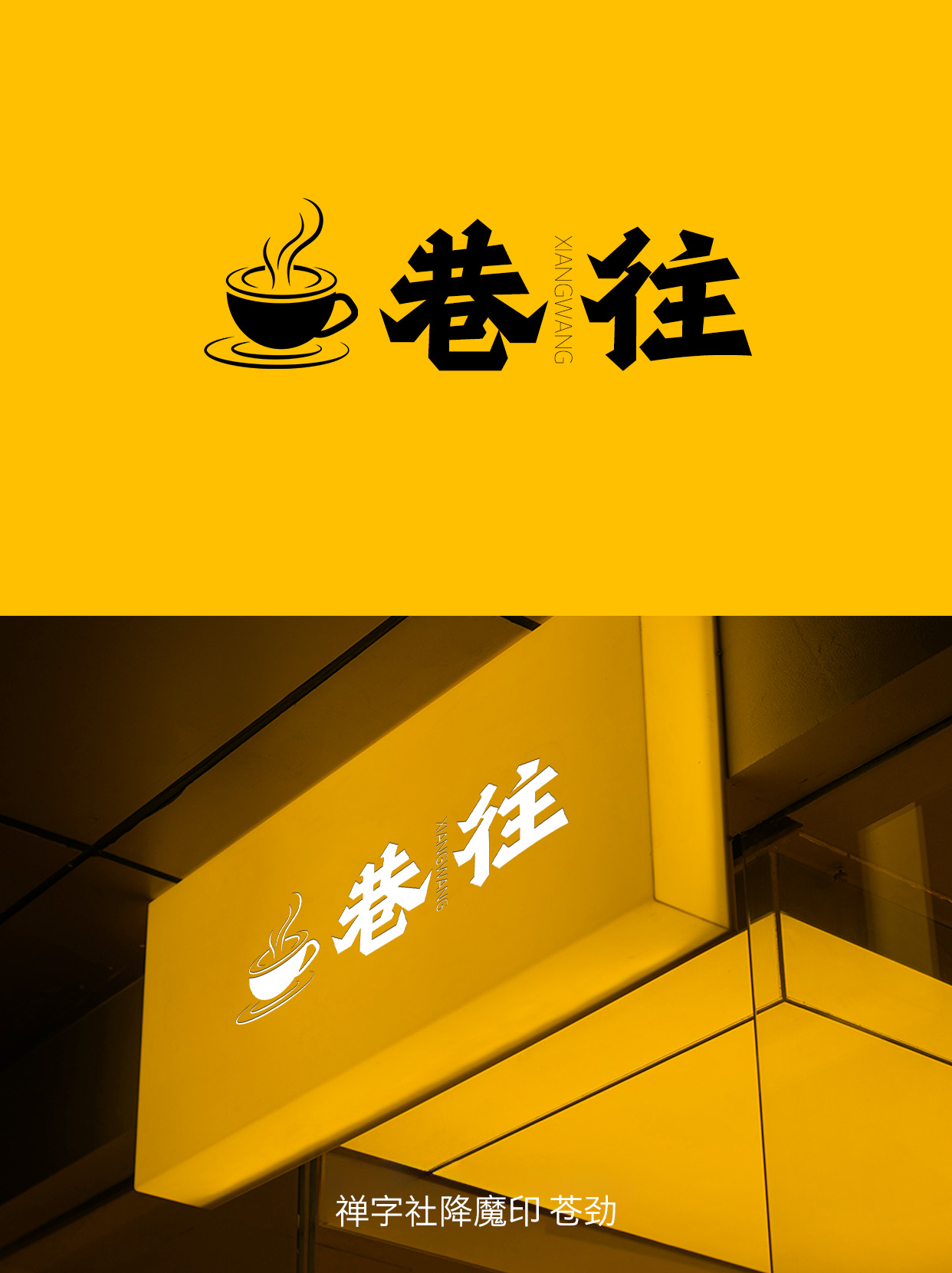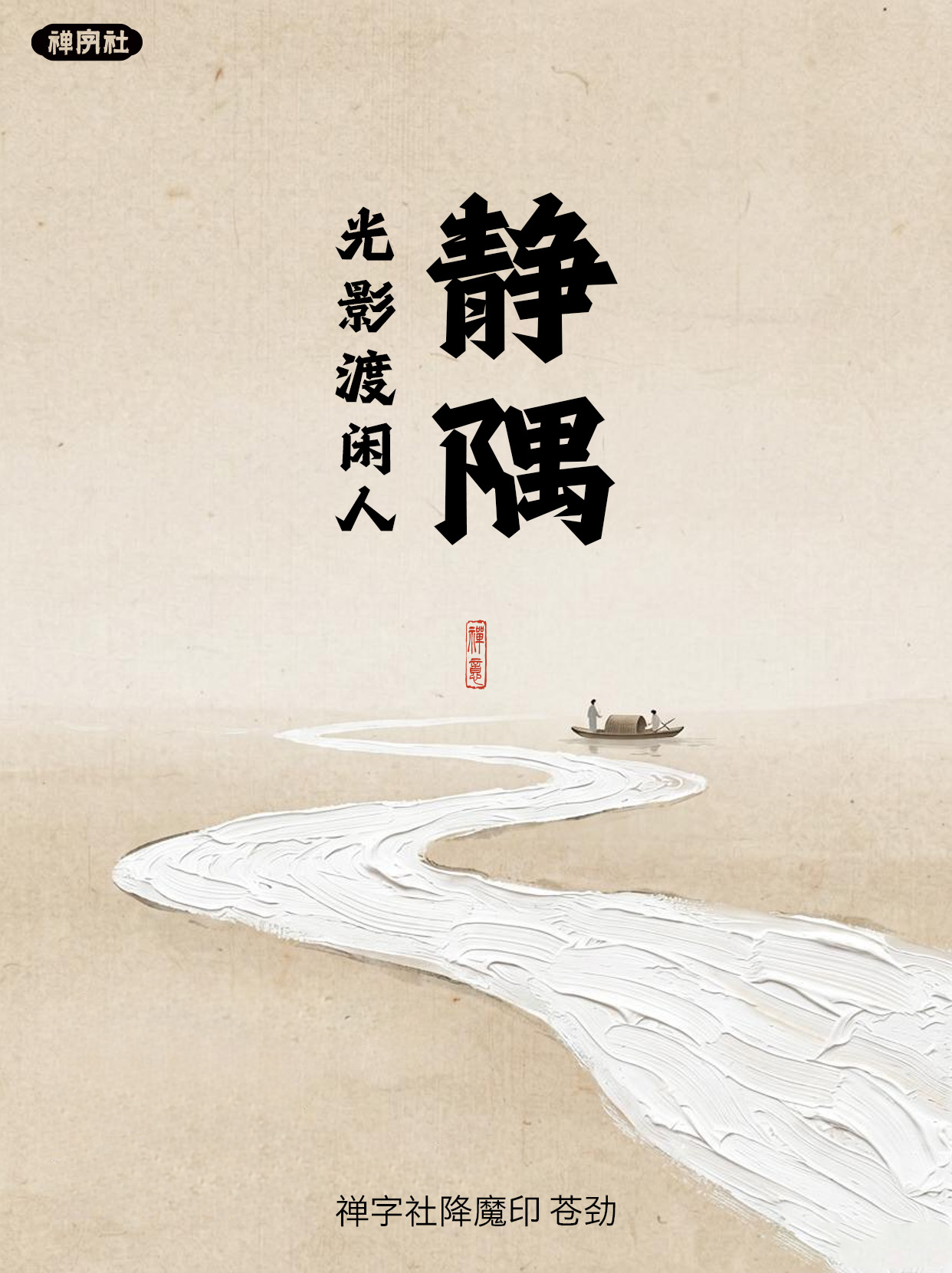
禅字社降魔印 苍劲
Zentype-XiangmoGB-Black
禅字社降魔印 苍劲兼具传统书法和现代个性审美韵味,是一款以楷书为基础,化曲为直、风格硬朗沉稳的书法创意字体。 整个字体偏硬朗,粗中有细,并具备向右上倾斜的态势。笔画逆锋起笔,棱角分明,行笔强调牵丝连带,收笔带有魏碑横笔厚重的特点。笔画力量饱满和收笔的上挑特点呈现出极具张力的字体风格。